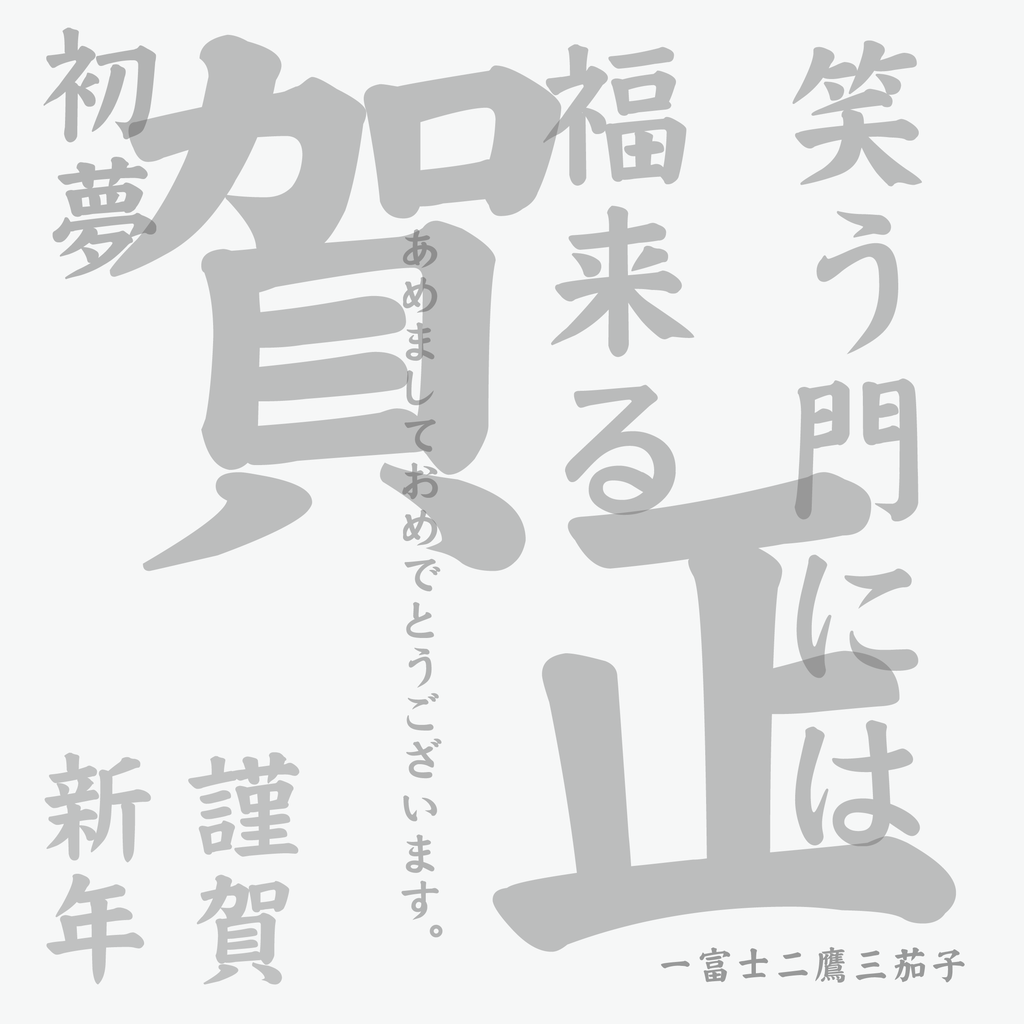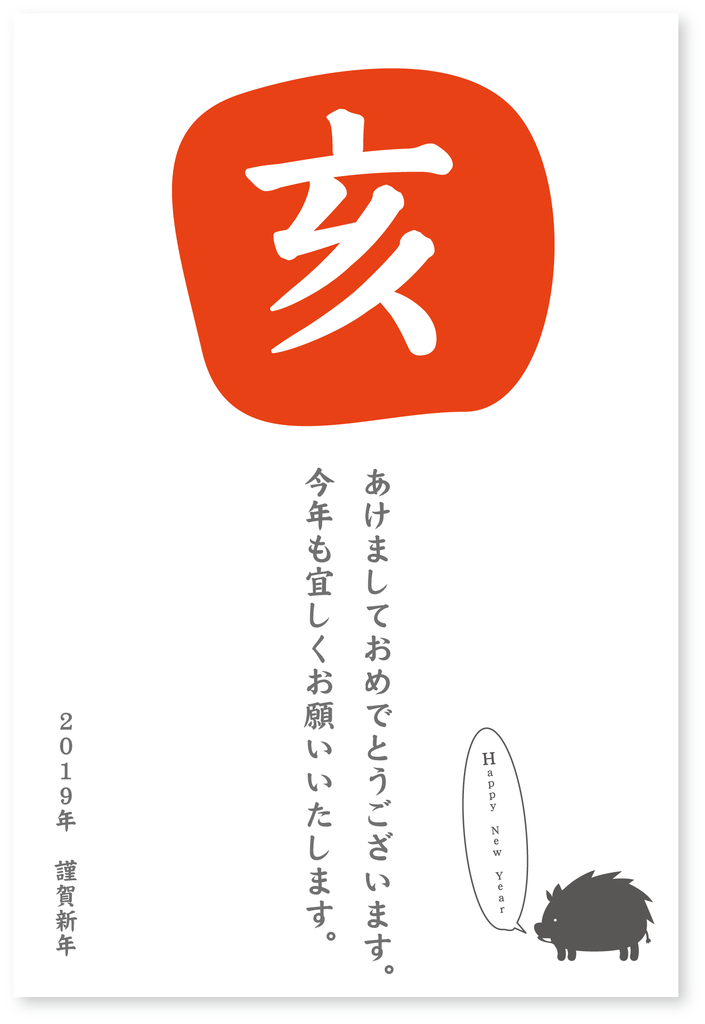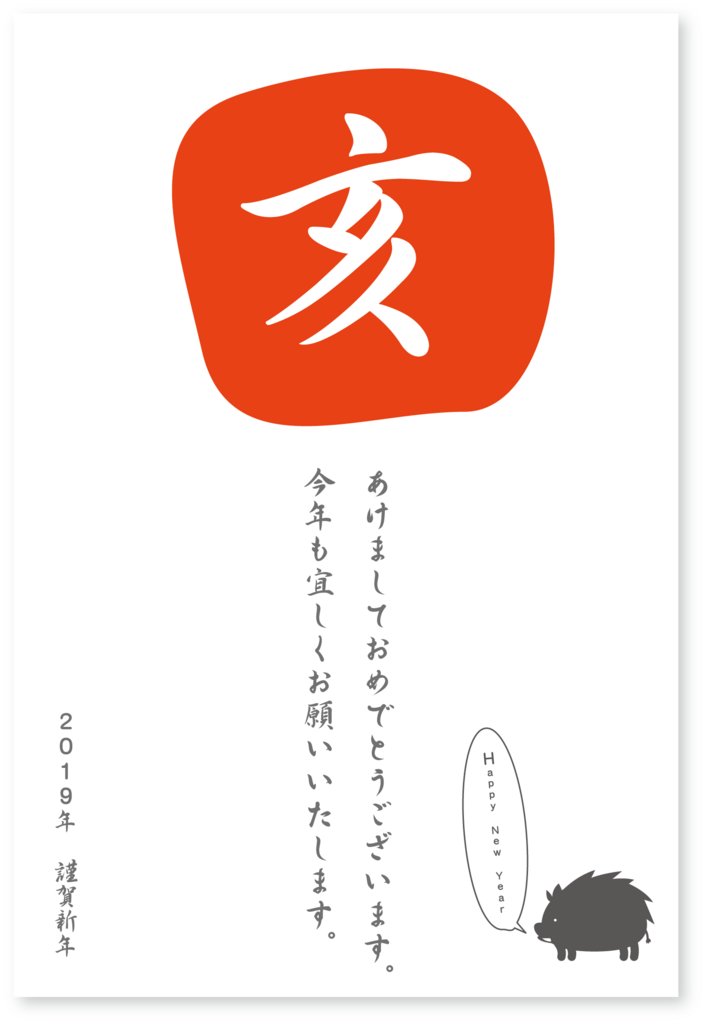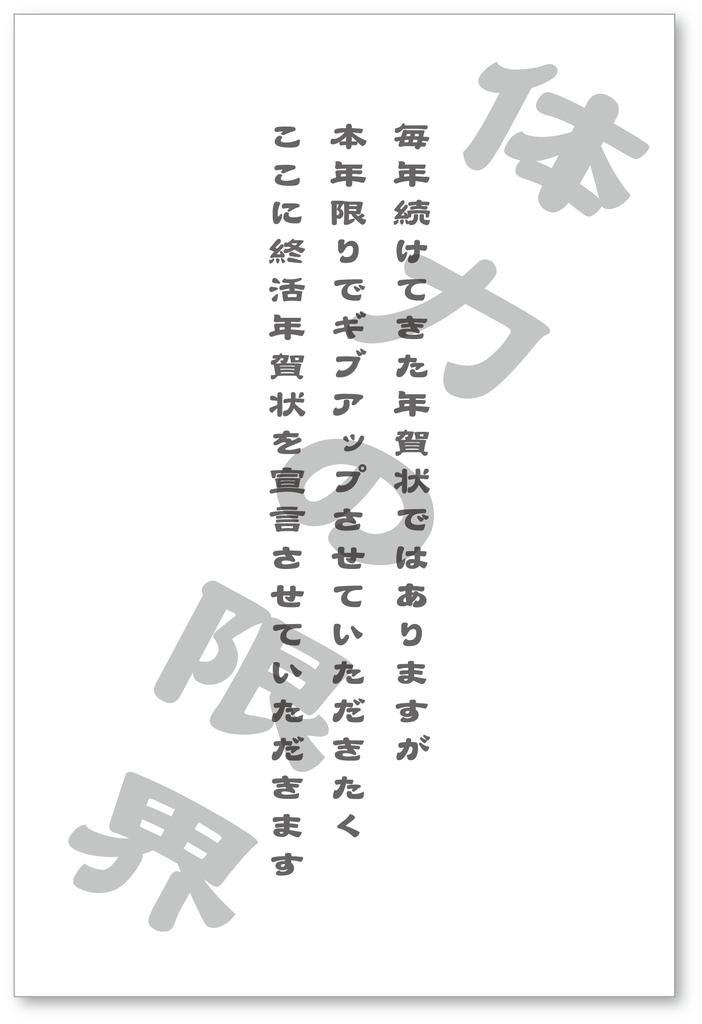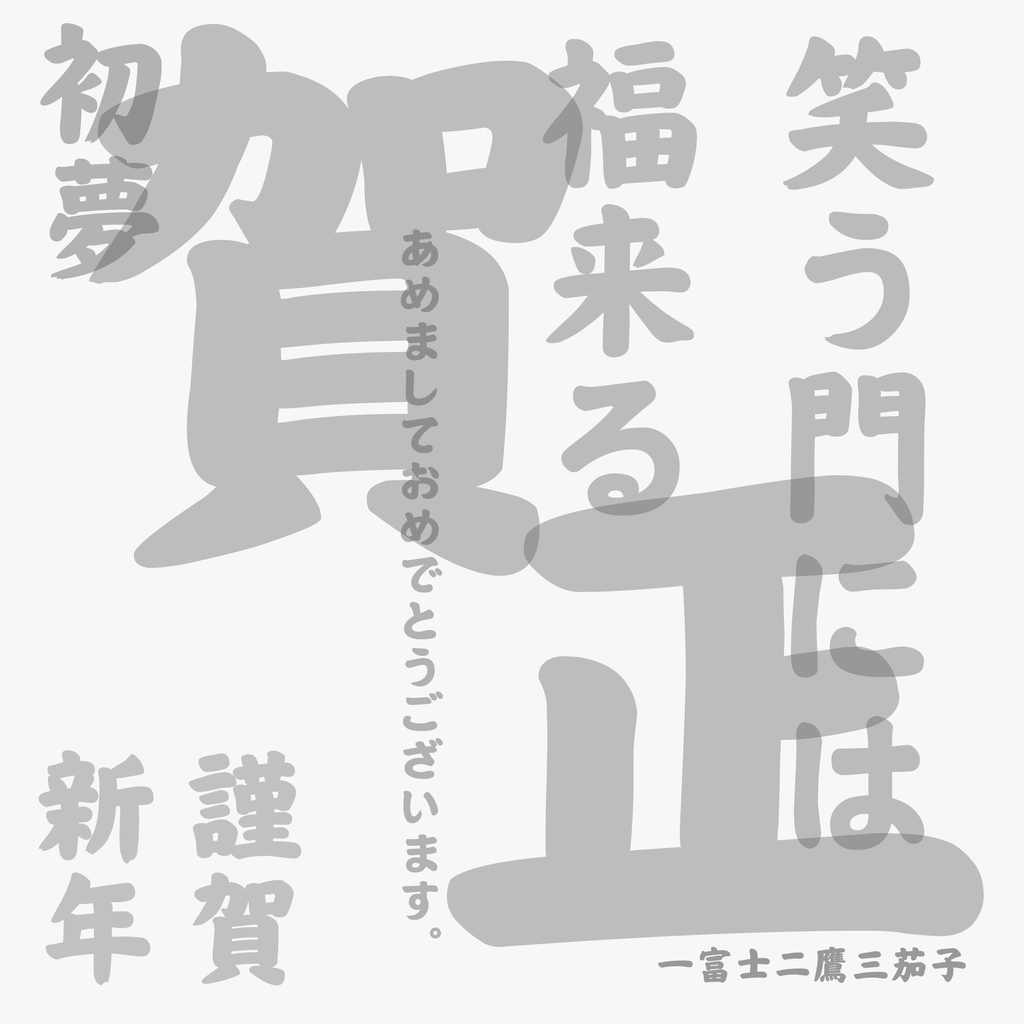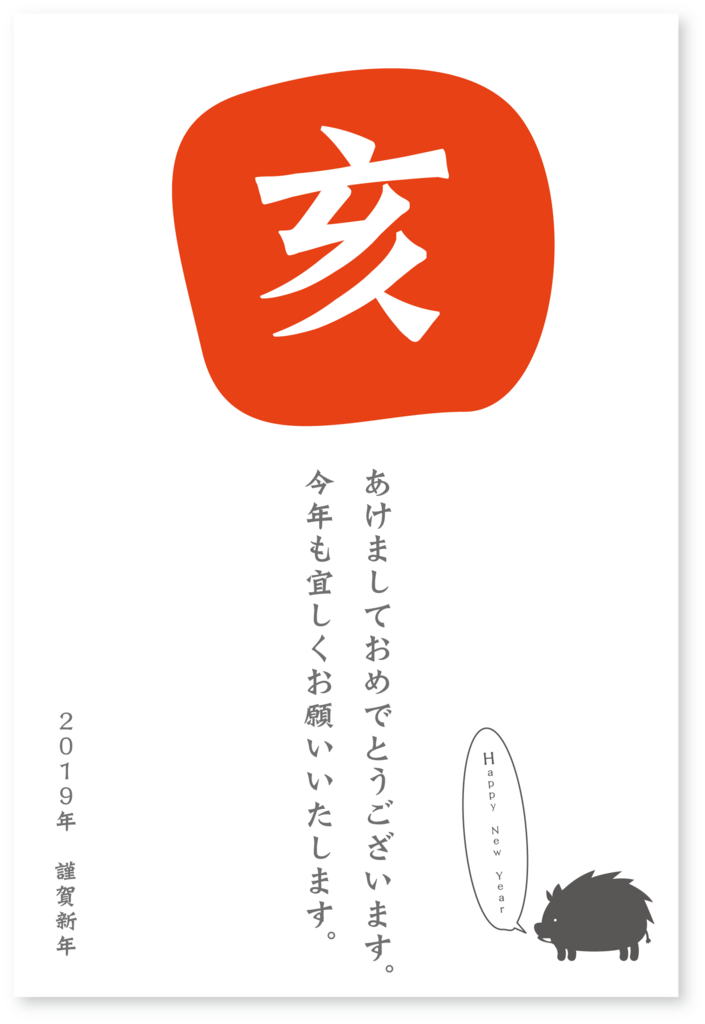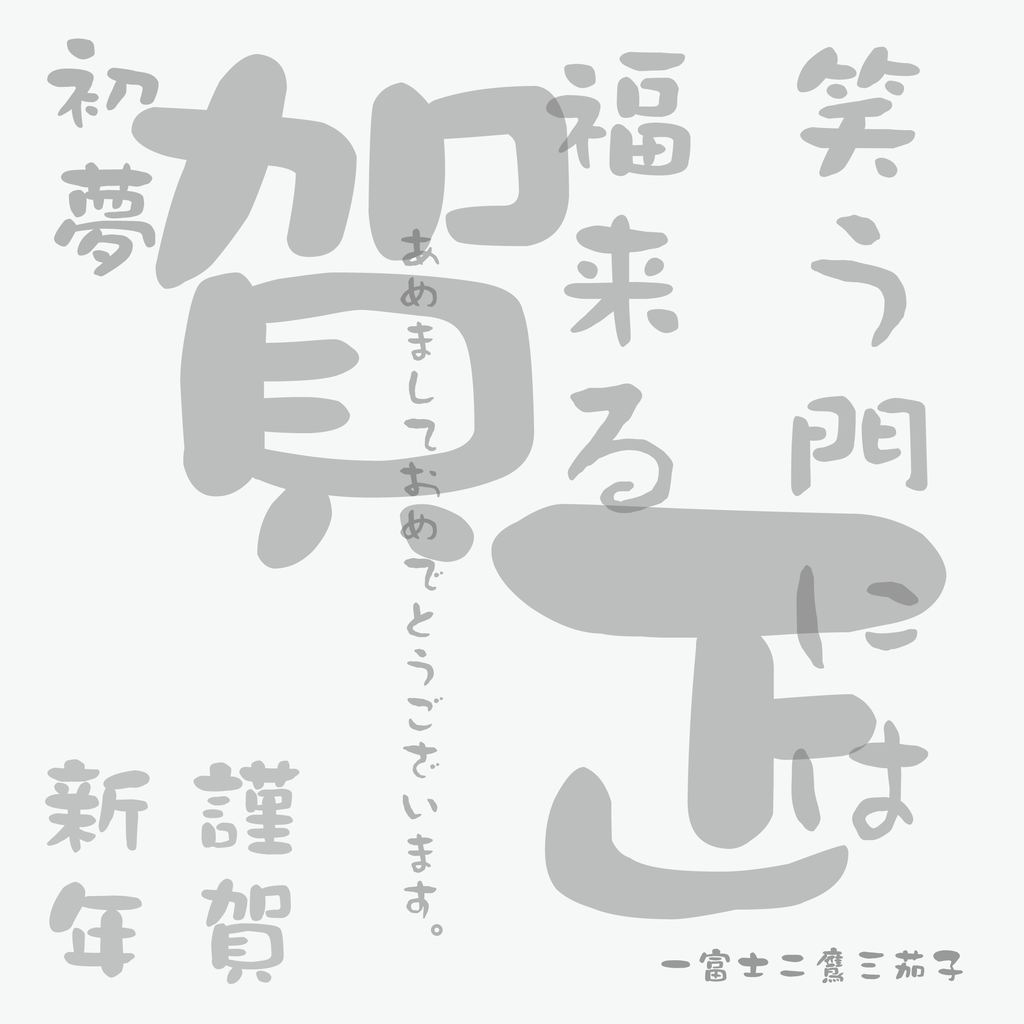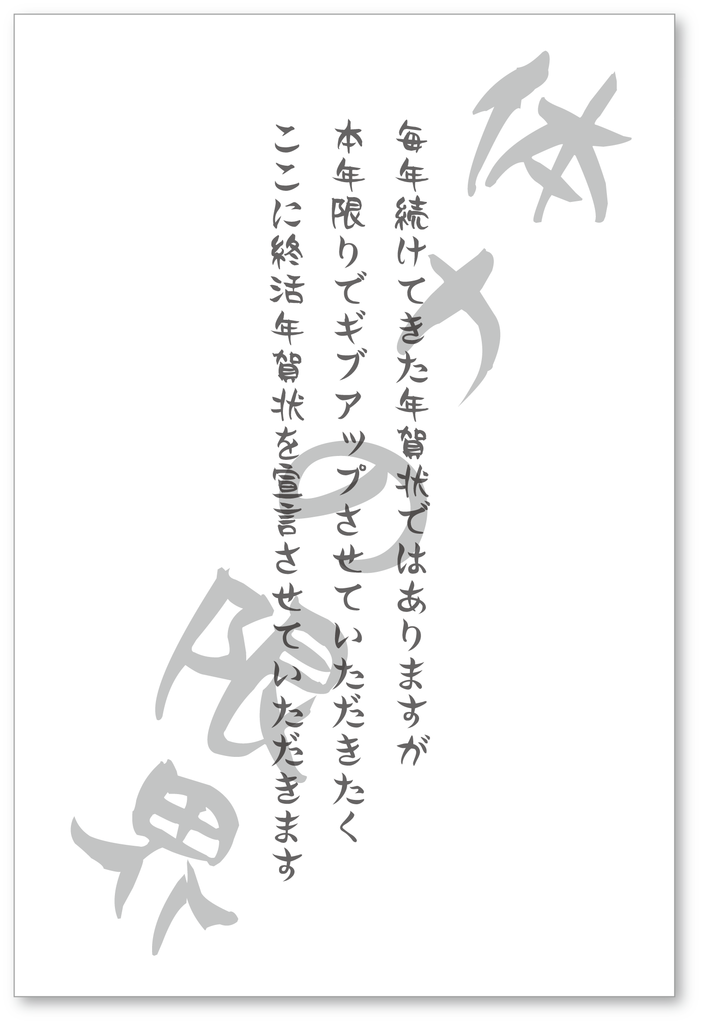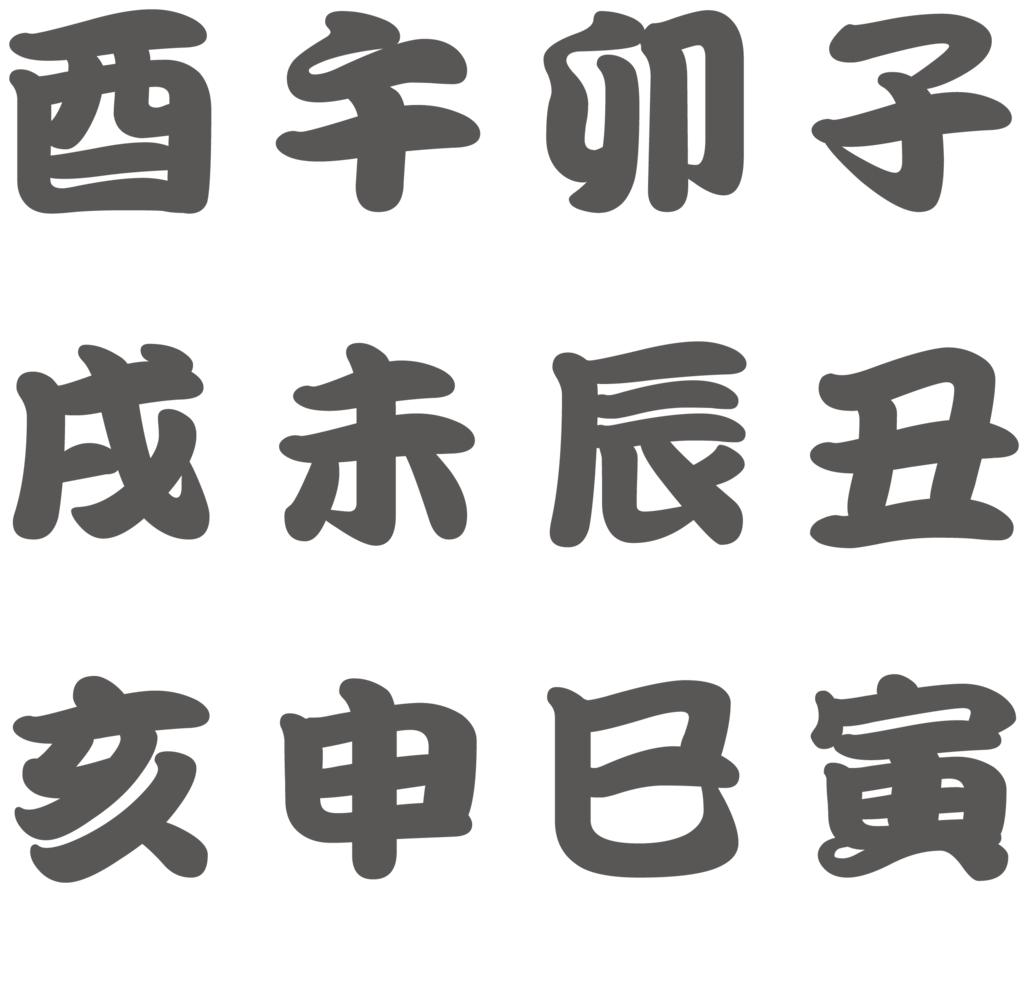
令和に年賀状なんてもうえーわ(令和)!なんて言わずに、令和も続く「年賀状」に適した筆文字書体(筆文字フォント)/墨文字書体(墨文字フォント)を紹介
SNSが台頭し、年々、廃れつつある年賀状であるが、まだまだ年始の挨拶として有効である事は間違いない。
そこで、今回は年賀状にお勧めの筆文字書体(筆文字フォント)をピックアックしてみた。
年賀状の記事について毎年更新していくのも面倒なので、猪の「亥」年だけでなく、ネズミの「子」年、それ以降の丑・寅・卯・辰・巳・午・未申・酉・戌、そして周りまわって「亥」年まで使えるように書けば、来年の事を言えば笑う鬼も目を回す事だろう。
そういうわけで、念願叶って書いているわけでもなく、いざ書き始めようとすると少し憂鬱にもなるのが年賀状について、その年賀状を作る際に使う書体を筆文字書体(筆文字フォント)に重点を置いてピックアップしてみた。
筆文字書体(筆文字フォント)といえば、ダイナフォントがラインナップが揃っている気がするので、ダイナフォントのパッケージに収録されている書体からオススメしたい筆文字書体(筆文字フォント)を独断と偏見で厳選してみたので紹介したい。
鬼滅の刃でお馴染みの昭和書体の鬼滅フォント「黒龍爽」で年賀状
「黒龍」は、牡の龍が暗雲立ち込める空を荒々しく漂うさまをイメージして作られた筆書系デザイン書体。
太い線と細い線が入り混じる緩急のついた画線は、まるで猛々しい龍の感情の抑揚を表わしているかのようです。正方形を意識しすぎることなく、ダイナミックに描かれた一つ一つの文字は、一見、アンバランスにも見えるが、文章として組むとその力強いイメージで見事に調和。
「黒龍爽」では、従来の書体である「黒龍」のカスレを少なくし容量を抑え、カッティングや動画にも使いやすくなっている書体となる。
鬼滅の刃でお馴染みの昭和書体の鬼滅フォント「心龍爽」で年賀状
「心龍」は、穏やかな牝の龍が天空から語りかけるイメージで作られた筆書系デザイン書体。
細い画線で、文章に使用すると厳かでありながら、優しいイメージを持たせる事が可能。
「心龍爽」では、従来の書体である「心龍」のカスレを少なくし容量を抑え、カッティングや動画にも使いやすくなっている。
筆文字書体「超極太楷書体」で年賀状/終活年賀状
大見出しに活用するために作られた楷書体で、オーソドックスな構成と筆法で書かれており、他の楷書体がもつ灰汁の強さを極力押さえている。
筆文字書体「華康楷書体」で年賀状/終活年賀状
堂堂と伸びた縦画が力強く、同時に格調高い、日本の伝統的な楷書と中国の楷書の流れを汲んだ楷書体。
筆文字書体「円楷書」で年賀状/終活年賀状
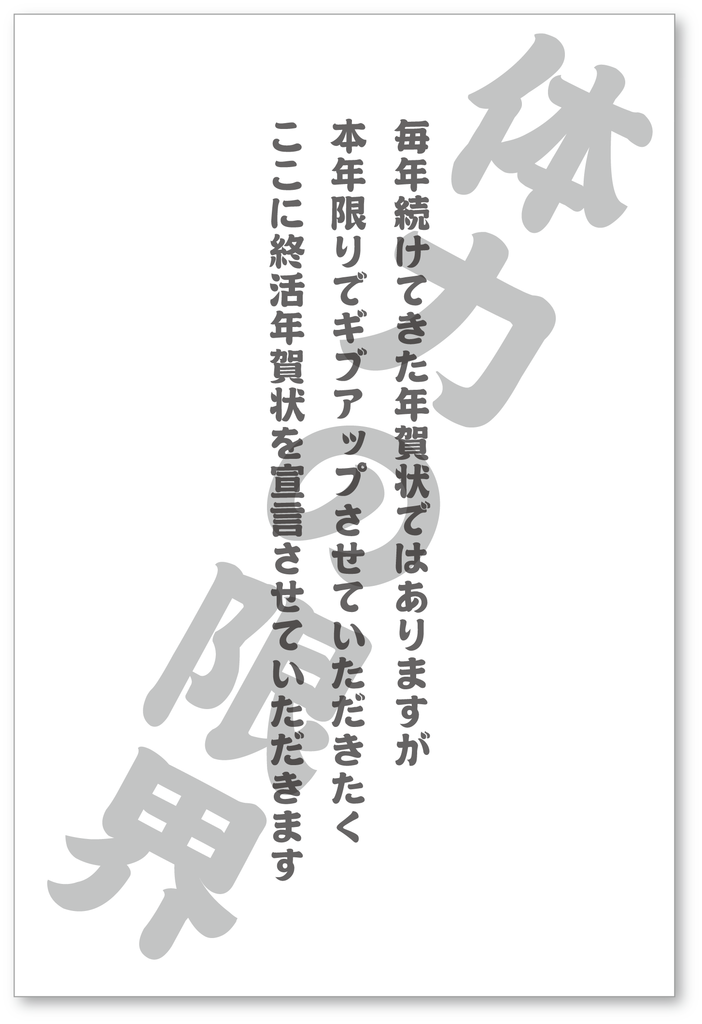
太く丸みのある筆勢で、穏やかな一面と力強さを表現した楷書体。
筆文字書体「談楷書」で年賀状/終活年賀状
清末民初の弘一法師の写経文字をモチーフに、フォントデザイナーによるオリジナルデザインが加えられた書体。
筆文字書体「麗楷書」で年賀状/終活年賀状